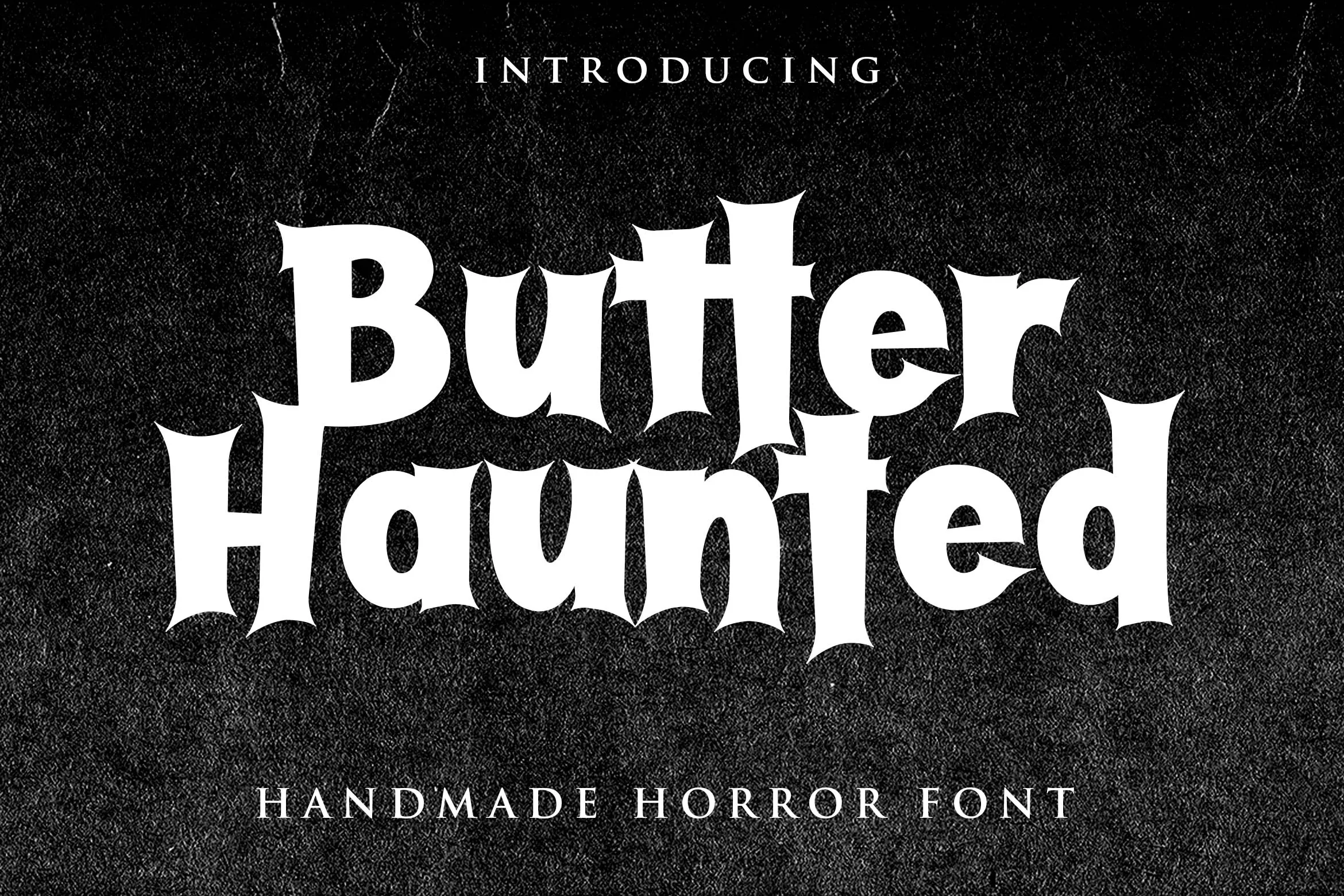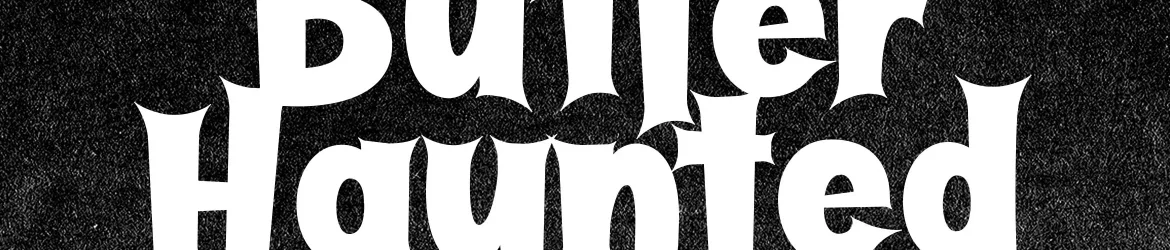
Olá, designers! Estou aqui uma nova adição para seu guarda-roupa criativo de tipos de letra: a Fonte Butter Haunted Display. Ela traz para você um charme assustador na categoria das fonts serif. Inspirado no designer Lettersiro, esta fonte tem o poder de transformar qualquer momento em horror com seus detalhes elegantes e arrepiantes. Escolha uma imagem sinistra para seu próximo projeto, seja a confeccão de roupas sobrenaturais ou até mesmo a criação de posters de filmes horripilantes. A Fonte Butter Haunted Display é um must-try para qualquer designer que procura dar vida às suas ideias com estilos arrepiantes e sofisticados. Que tal incorporar o pesadelo no seu próximo projeto? Não perca tempo, é hora de trazer a essência do horror à vida através de seu design.